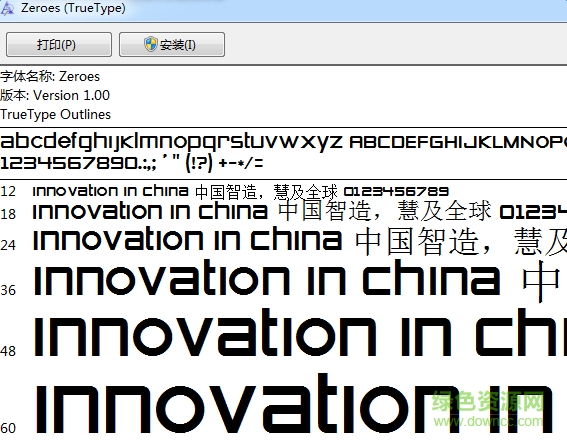
zeroes字體是一款超好用的英文個(gè)性字體,該字體比較扁平,卻又不失風(fēng)格,簡(jiǎn)單的筆畫透露出不一樣的氣息,需要的用戶就趕快來綠色資源網(wǎng)免費(fèi)下載收藏吧!
zeroes字體是一款極具個(gè)性的字體,該字體十分飄逸,彰顯了自己的個(gè)性,有喜歡的朋友可以來綠色資源網(wǎng)下載使用!